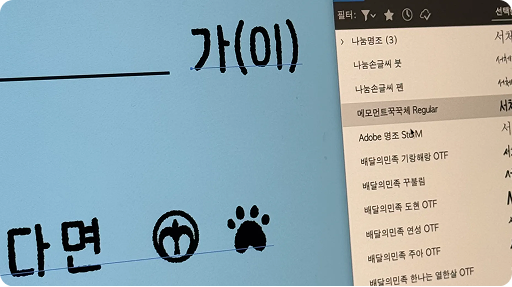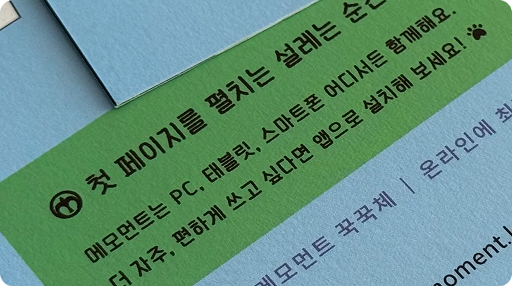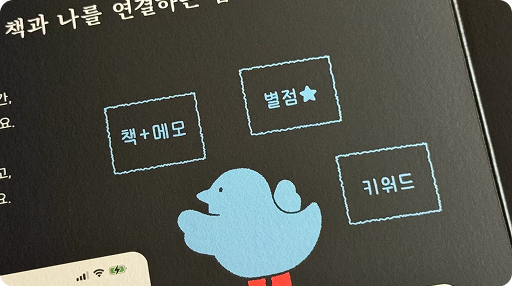
메모먼트 꾹꾹체
기록은 마음을 꾹꾹
눌러 담는 일이니까요.
메모먼트 꾹꾹체는 AI기록앱 memoment의 손글씨 기반 글꼴입니다. 디지털 화면에서도 읽기 쉽도록 자간과 획의 균형을 조정했으며, 단정하면서도 따뜻한 인상을 주는 형태로 완성했습니다.
♧ 입력 시, 냥이 발바닥이 꾸욱, 나타납니다.
메모먼트 꾹꾹체는 기록의 감성과 경험을 더 많은 사람들과 나누기 위해 제작되었습니다.